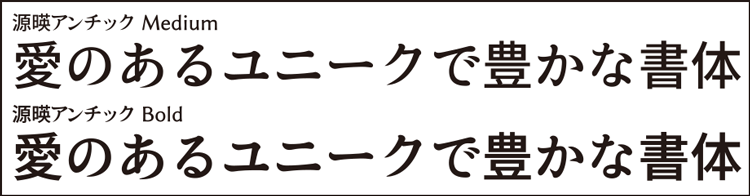
源暎アンチックは、漫画向けフォントとしてメインで使われるアンチゴチのフリーフォントです。アンチック体の仮名と、ゴシック体の漢字を組み合わせたフォントで、漫画の吹き出しのセリフに使われます。漫画で一般的に使われるアンチゴチフォントの中でも細身なフォントで、絵に大して主張しすぎない、バランスのいいフォントに仕上がっています。
アンチック体のフリーフォントは数が少なく、とても貴重です。多くのフリーフォントはクセが強かったり、収録文字数が少なかったりして使いにくいものが多いですが、その中でもこの源暎アンチックはバランスがよく、収録文字数も十分です。
オープンソースフォントの「新コミック体」をベースに、漢字と仮名が同じ太さに見えるように調整するなど細かな改変が加えられています。漢字はGoogleとAdobeが共同開発したオープンソースフォントの「源ノ角ゴシック」が使用されてり、JIS第四水準までカバーしています。
ベースの「新コミック体」
改変を加えた「源暎アンチック」
欧文フォントは、サンセリフ体の「Linux Biolinum」をベースに調整を加えています。
アンチック体フォントの「GL-アンチック」から、漫画用記号として有名な顔付満月、怒りマークなどいくつかの記号が使用されています。また、「?」は漫画で一般的なケルン付きに変更され、「!」と組み合わせた合成済み文字の正体、斜体がそれぞれ用意されています。
通常のMediumウェイトに加えて、Boldウェイトが用意されています。